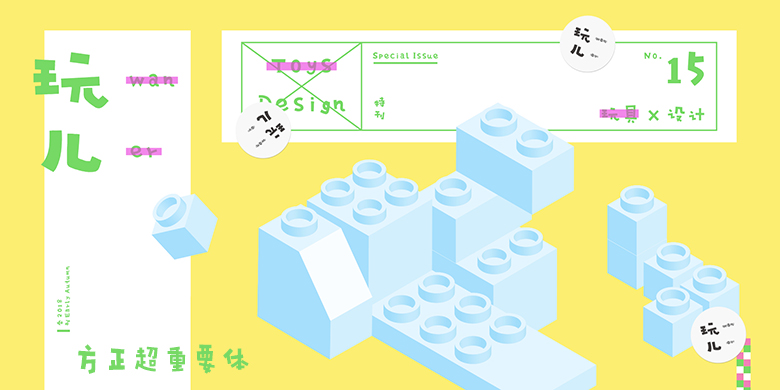
方正超重要体
品牌:方正字库设计师:张驰发行时间:2018字库编码:大陆简体(GB2312-80)、简繁扩展(GBK)分类:创意书写
方正超重要体是2018年7月方正字库最新开发的一款中文字体,设计师张弛是位漫画家,曾经画过一本叫做《消费侠》的绘本漫画,主角是个虽然本身一点都不重要,但因为大大咧咧的性格经常给周围的人带来困扰而莫名抢镜的人。为了配合角色的性格,于是在漫画使用了一些“看起来假装很重要”的字体。这款字体笔触粗实,具有很强的视觉感染力,看上去有种笨重的感觉,虽然我们并不知道这款字体对大家来说到底重要不重要,不过为了贯彻当初创作时的精神,还是要叫“方正超重要体”!重要!